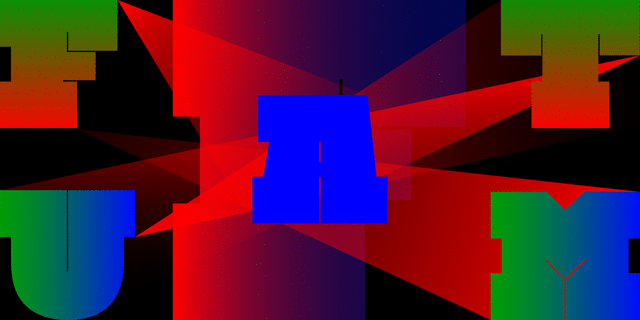
Шрифт разработан в фирме TypeMarket в 1993 (дизайнер A.Кустов) по рисункам шрифта Aachen (дизайнер К.Бригнелл, 1969).
Ассоциации c семейством LuxorКачества и характер:
сильный, мощный, техногенный, тяжелый, твердый, жесткий, острый, стальной, индустриальный, мужественный, устойчивый, статичный, стабильный, крепкий, внушительный, убедительный, авторитетный, настойчивый, ровный, четкий, качественный, звонкий, прямоугольный, серьезный, железный, надежный, уверенный, военный, армейский, солдатский, мотивирующий, ответственный, суровый, громкий, заметный, яркий, активный, броский, крутой, амбициозный, сексуальный, бандитский, рабочий
металлургия, машиностроение, техника, война, танк, инструмент, стройматериалы, строительство, камень, бетон, станок, бодибилдинг, тренажеры, завод, индустрия, промышленность, электростанция, энергетика, джинсы, армия, ремонт, револьвер, охрана, защита, страйкбол, полиция, стройка, блокбастер, боевик, экшен, обувь, регби, кирпич, грузовик, дальнобойщик, сталевар, мотор, двигатель, технологии, рабочий, локдаун, нефть, селфи Стилистика:
Особенности семейства LuxorХит десятилетия:
Хит 1990-х Близкий исторический оригинал: